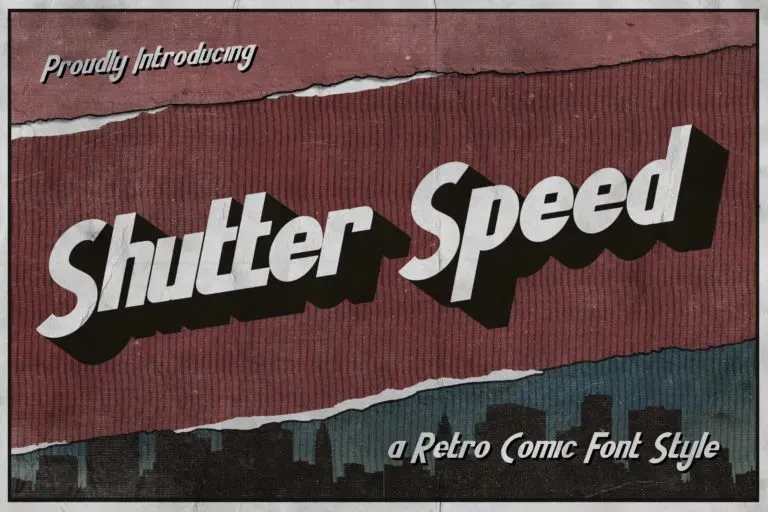
A Shutter Speed Font é uma elegante fonte sans-serif que nasceu da criatividade do tipofactory, com um toque vintage e textura de selo. Essa fonte é perfeita para os projetos mais variados: desde editoriais de moda e revistas até logotipos, marcas, convites de casamento, citações, cabeçalhos de blogs, cartazes, anúncios, cartões postais e até mesmo capas de livros ou websites. Suas linhas retas e modernas facilitam o uso em qualquer formato visual, garantindo um equilíbrio entre elegância e simplicidade. Ideal para quem busca uma fonte clara e versátil para seus projetos digitais e impressos. Que tal adicionar a Shutter Speed à sua seleção de recursos gráficos?